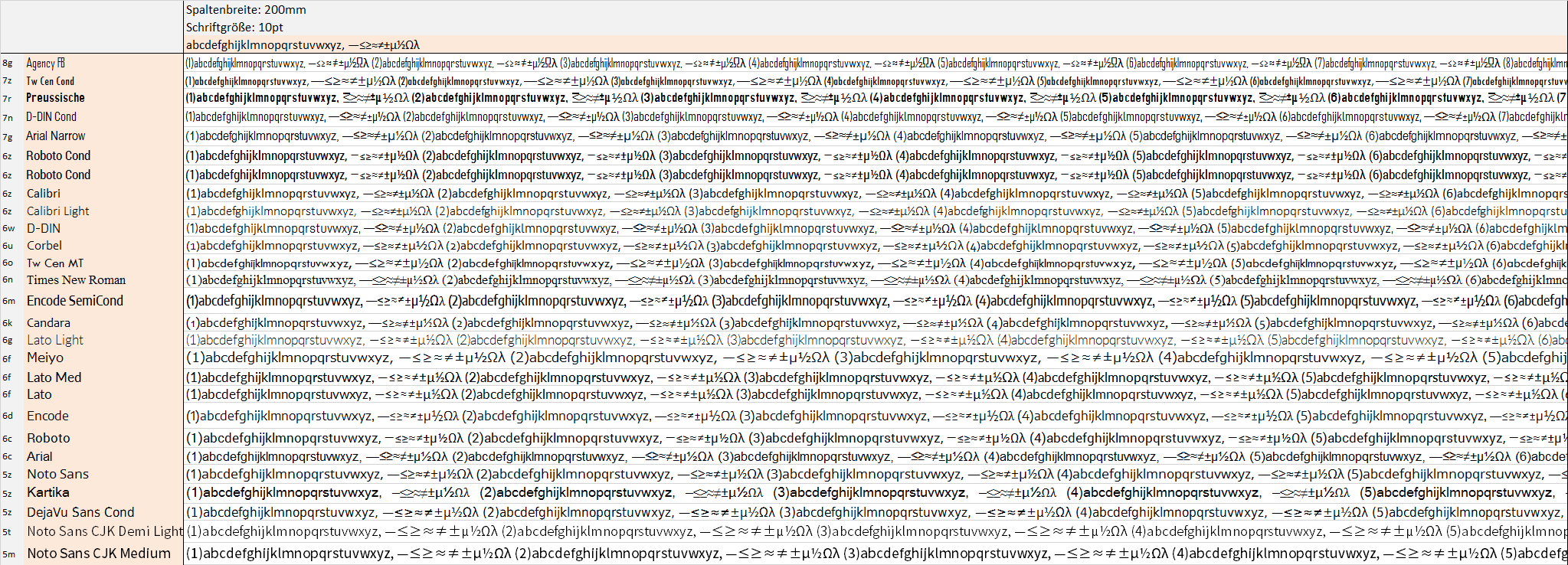
Sehr sachliche und flexible (und freie) Grotesk gesucht
habe schon etliche Kandidaten, die OK wären, aber alle nur zu 80% passen.
Ich suche eine Standardschrift für technische Unterlagen, die auch  veröffentlicht werden. Also sollte sie folgendes erfüllen:
- kostenlos
- sehr sachliche Erscheinung
- im Normalschnitt einigermaßen platzsparend, da vielfach in Tabellen eingesetzt. Oder eine Familie mit schmaler Schnittvariante, die "nicht zu gepreßt" wirkt als Tabellenschrift.
- Mehrere Schnitte (bold- thin)
Ich habe auch schon mal mit DIN-Schriften experimentiert, sind die mit aber doch zu "unintuitiv" für den Leser und zu fett. Die Schrift sollte wirklich sehr sachlich, technisch, harmonisch und unauffällig sein. Und dabei maximale Flexibilität (Schnitte, Sonderzeichen) bieten. Alles was z.B. in Richtung Lucida etc. geht ist mir schon zu verspielt... Gilt z.B. auch für Noto Sans, die ich gerade behelfsmäßig verwende.  (Normal hat außerdem nur einen Schnitt, CRJ immerhin verschiedene Schnitte aber riesige Zeilenhöhen...)
Warum muss es eine kostenlose sein?
Henne-und-Ei-Problem:
Ich habe derzeit kein Budget, eine anzuschaffen. Sofern das Ergebnis überzeugt und sich bewährt, ist der Preis egal, Schriften kosten ja nicht die Welt. (Am liebsten wäre mir ehrlich gesagt die Möglichkeit, später zu einer „sehr ähnlichen“ kostenpflichtigen zu wechseln, um eine professionellere Lösung zu haben.)
...das heißt, auch kostenpflichtige Vorschläge sind sehr willkommen. Ich brauche aber jetzt aktuell erstmal eine kostenfreie Schrift.
Danke für die Vorschläge. Beide sind tatsächlich echt gut. Lato erscheint mir mit den gleichmäßigeren Strichstärken noch etwas sachlicher. Dafür hat Fira Sans mehr Varianten, aber fünf Stärken von Lato genügen mir eigentlich...
Schön wäre allerdings noch eine Semi-Condensed-Variante  die nicht zu dünn erscheint um Platz zu sparen. Muß mal ausprobieren, wieviel mit der Regular im Vergleich zu anderen Schriften in eine Spalte paßt. Benchmark ist hier für mich die (unterschätzte?) Arial Narrow, die ich zwar eigentlich mag, aber doch sehr "narrow" aussieht. So eng muß es nicht sein.
Lato ist leider nicht wirklich soo platzsparend. Läuft selbst als Thin breiter als  z.B. Calibri.
habe schon etliche Kandidaten, die OK wären, aber alle nur zu 80% passen.
… die da wären? Dann brauchen wir die gar nicht erst nennen.;-)
Thin ist ja auch nur die Strichstärke – auf die Laufweite hat das nur bedingt Einfluss …
Ansonsten: Myriad – ist beim Adobe Reader dabei oder per Typekit :-?
Oder PT Sans :-? Kostenlos, verschiedene Schnitte und auch Narrow …
Muss es denn Sans sein?
Wenn die Noto schon zu verspielt ist, bewegen wir uns beim Thema Leserlichkeit aber in die falsche Richtung. Auch technische Unterlagen wollen möglichst leicht gelesen werden, um nicht den ohnehin schon trockenen Inhalt nicht noch schwerer verdaulich zu machen …
stimmt, hätte ich eigentlich auch schreiben können, was ich so ausprobiert habe.  Mach ich später novh.
Myriad und PT Sans gefallen mir beide gut, hatte ich noch nie ausprobiert. Aber für diesen  Zweck kann es gerne noch strenger und sachlicher sein. Im Grunde kommen auch Serifen-Fonts infrage, aber ich finde, da ist die Gratwanderung zwischen sachlich streng und harmonische&lesbar schwieriger. Für gute Vorschläge bin ich aber offen.
Es soll halt "neutral, sachlich , professionell, kompetent, präzise,..." wirken und gleichzeitig etwas schlanker ausfallen (Platz in Tabellen). Und gleichzeitig harmonisch und lesbar sein.
Äh, das war vielleicht etwas viel. Also schlicht eine gute, sehr streng sachliche und schlanke Schrift. Nicht so exotisch, daß Sonderzeichen und Schnitte knapp ausfallen.
R::bert: Alle, die die Schrift nutzen, arbeiten mit Win7.
bertel: Ich bin typographischer Laie, glaube aber, daß ich verstehe was Du meinst.
Letzlich wäre etwas wie Noto, Lato, Myriad, schon OK. Nice-to-have wäre noch etwas mehr technische Strenge. Wichtiger ist mir aber die Möglichkeit in Tabellen Platz zu sparen ohne an Laufweite drehen zu müssen oder dünne Strichstärken zu nehmen. Eine schmal ausfallende Schrift oder eine mit semi-condensed-Variante wäre schön.
Encode gefällt mit sehr (für diesen Zweck). Hoffe Sie fällt im Test so aus wie im ersten Eindruck.
War erst enttäuscht, daß sie nicht wirklich schmal ausfällt. Dann habe ich die Schwesterfonts semi-condensed etc. entdeckt. Super flexible Familie!
Habe Encode Sans getested:
In semi-condensed als nicht zu gepreßt wirkende  Tabellenschrift perfekt.
Vielen, vielen Dank für die D-DIN. Die ist großartig. Ganz allgemein, aber  eigentlich auch und gerade für diesen speziellen Zweck.
Leider gibt es sie nicht in semi-condensed. Das schränkt die Flexibilität etwas ein.
Hab noch mal schnell die Breite einiger Schriften verglichen. Anbei mein Vergleich. Von den Normalschnitten sind ja D-DIN und überaschenderweise Calibri extrem platzsparend...